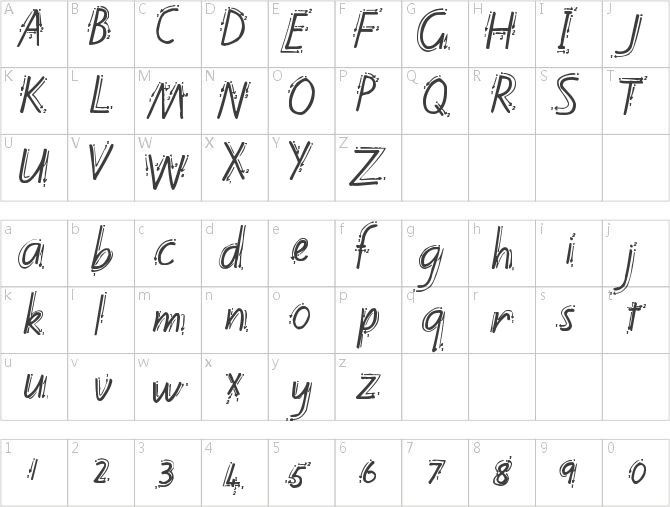
字体名称: kiwisch
kiwischoolhandwritingwithguidesr
kiwischoolhandwritingwithguidesr字体字库是一款让人赏心悦目、百看不厌的英文字体,适合各类广告和产品包装设计应用,字体大小0.03MB,格式为ttf字体,上传用户是Apple,作者/版权方为未知